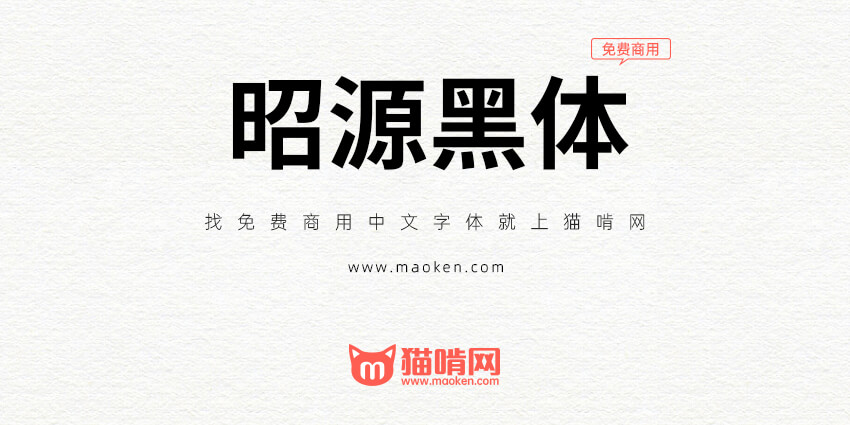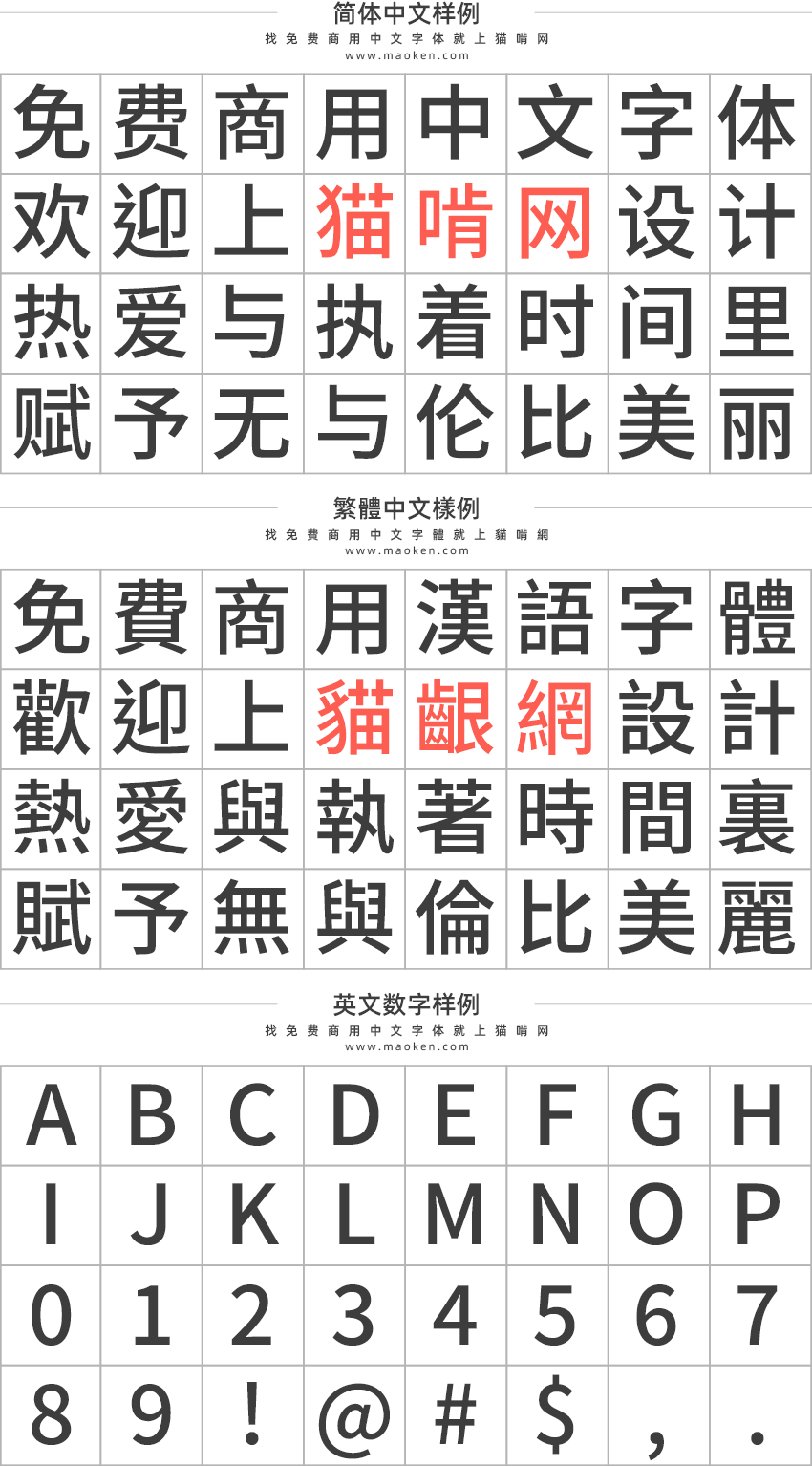
| 字体作者:tamcy (中国香港) | 字体字重:7个 |
昭源黑体是一款以思源黑体香港版为基础、採现代笔形风格、平衡标准字形和印刷体惯用笔形的免费开源黑体字型。跟思源黑体香港版一样,昭源黑体採用现代笔形,但在个别字形的式样上吸收了传统笔形的特徵,使之更适合作显示和印刷用途。
在香港,坊间採用现代笔形设计的商用字体虽然也有参考《常用字字形表》的写法、引入一些手写字体的元素,但仍会保留传统印刷字体的气韵,不会完全“楷书化”。昭源黑体的取态跟这些字体类似:本字体会参考《思源黑体 香港》中的香港标准字形和採现代笔形的商用印刷字体字形,提供一个“中间着墨”的开源字体方案。
昭源黑体提供和思源黑体相同的 7 款字重。除了个别中文字的字形经过修改,本字体的其他参数与思源黑体完全相同。
部分的字显示为日系字形,例如:画、会、遥等等,建议修复。
因為這箇字體根本就不是為簡中設計的 若在意這些請使用思源黑sc版
同理 專為簡體中文設計的字體裏面的繁體字,例如: 誤、窰、骨…等等 對於繁體中文用戶來說都是錯字 魚和熊掌不可兼得
在意錯字這些唯一解決方案 簡中用戶用專為簡中設計的字體 繁中用戶用專為繁中設計的字體